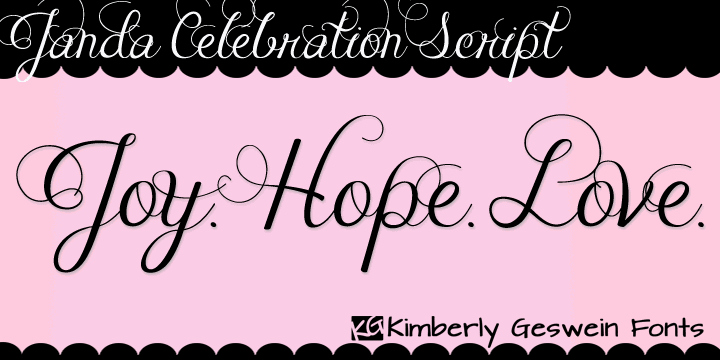
Janda Celebration Script font – Download Grátis
A fonte Janda Celebration Script é uma criativa escolha para qualquer projeto que deseja adicionar um toque de festa ao design. Criada pela designer Kimberly Geswein, essa fonte foi lançada em 2012 e ganhou destaque por sua elegância e personalidade vibrante. Ideal para textos interativos como gráficos de marketing ou materiais educacionais, a Janda Celebration Script oferece uma infusão de diversão com seus traços delicados e linhas levemente curvas. A fonte é perfeitamente adaptada para nomes de empresa chamativos, headlines de posts no blog ou até mesmo letras da letra do seu próximo single pop. Com sua capacidade única de capturar atenção, a Janda Celebration Script atende aos desejos de designers que buscam uma fonte versátil e cheia de vida. E se você está procurando por algo além de um simples texto, essa fonte também é excelente para criar elementos gráficos memoráveis como ilustrações ou infográficos. Seja um designer profissional ou um amante da criatividade que busca algo único e divertido para seus projetos, Janda Celebration Script é uma opção inegável.